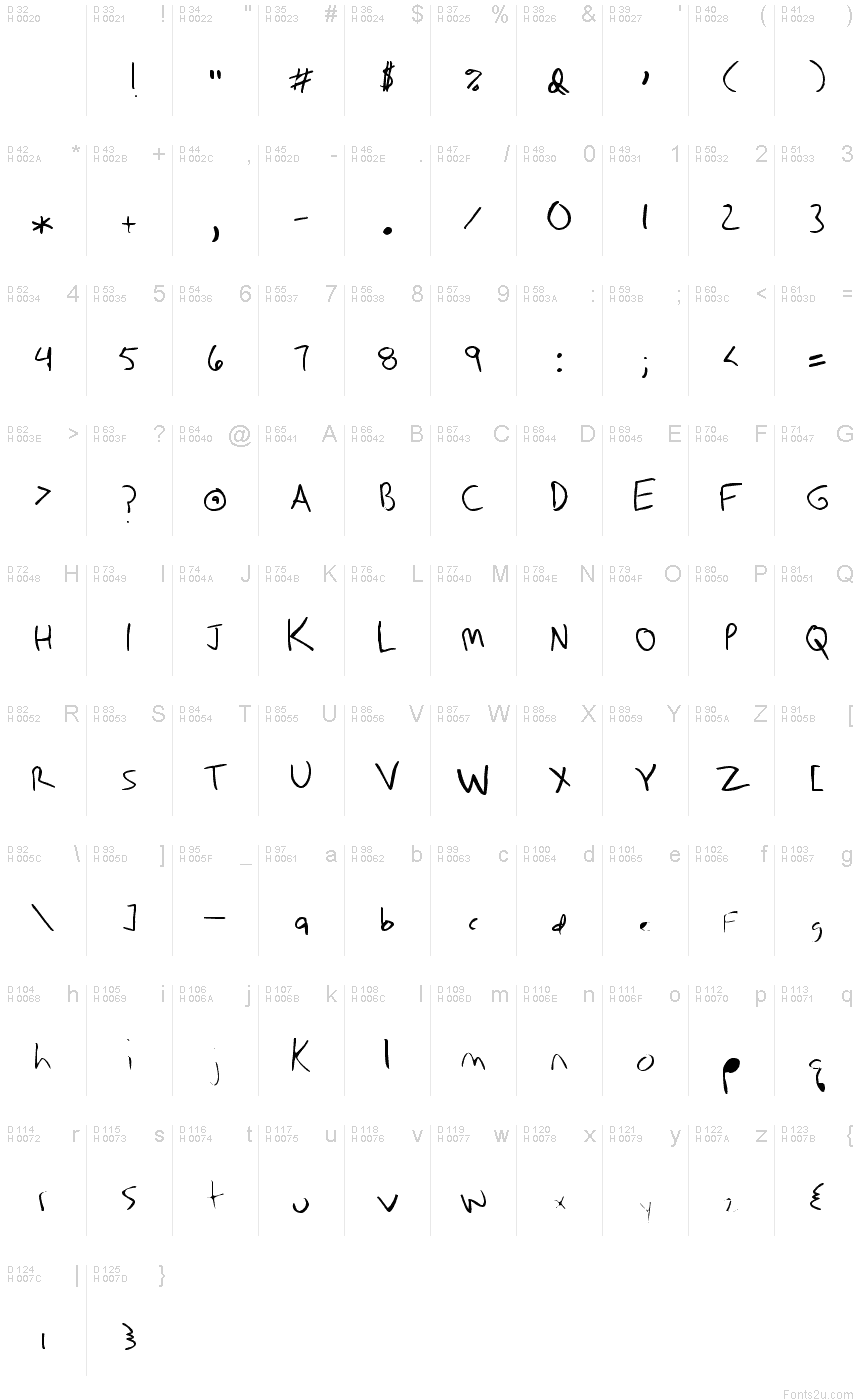
تُعد AndyHand، التي صممها Andy Krahling، خطاً مجانياً مكتوباً بخط اليد يجسد العفوية الحرة ولمسات الحبر المعهودة في الملاحظات السريعة على قصاصات الورق. وتمنح حروفه الطويلة والمرتجفة قليلاً وضرباته غير المتساوية طابعاً شخصياً وعفوياً لا يشبه الخطوط الرقمية المنسقة بدقة. وتتميز المسافات بين الحروف بأنها مفتوحة بما يكفي للحفاظ على سهولة القراءة، مما يمنحك ذلك الطابع الإنساني غير المتكلف دون التضحية بالوضوح في النصوص الطويلة.
يتألق خط AndyHand في تصاميم اليوميات، والمدونات الشخصية، وملصقات الـ doodle، والمواد التعليمية، ومنشورات وسائل التواصل الاجتماعي، وتنسيقات المجلات المستقلة (Zines). إنه يعمل بشكل رائع أينما كنت تبحث عن لمسة صادقة، غير مثالية، وتمتلك طابعاً فريداً. جرب دمج AndyHand مع خط sans serif هندسي بسيط للنص الأساسي، واترك لـ AndyHand مهمة إبراز العناوين والاقتباسات والتعليقات بأحجام أكبر قليلاً للحصول على أقصى درجات الجاذبية.